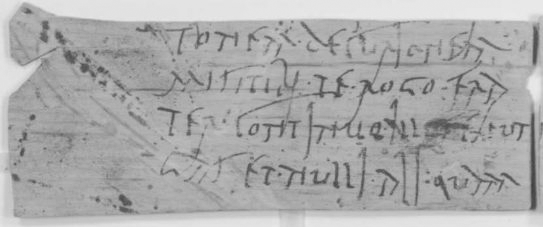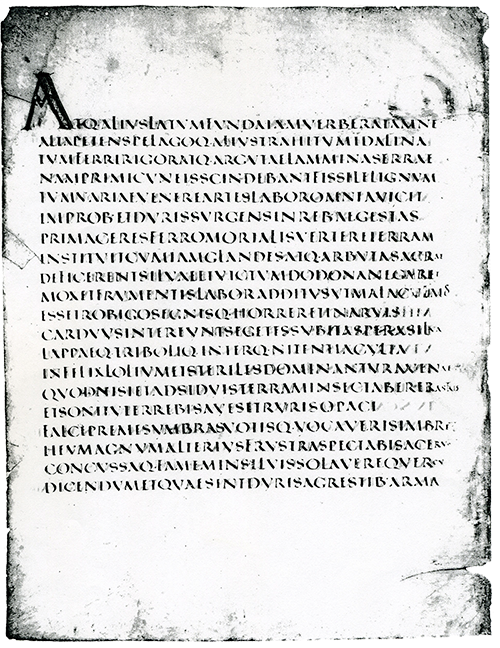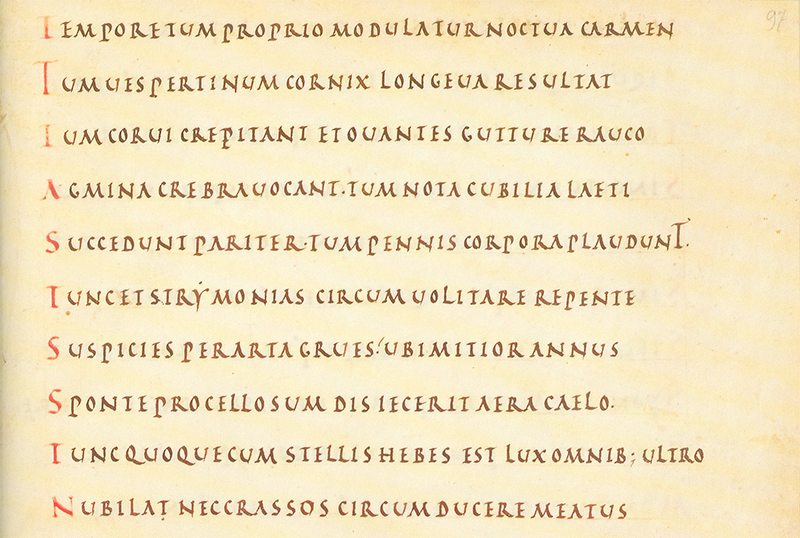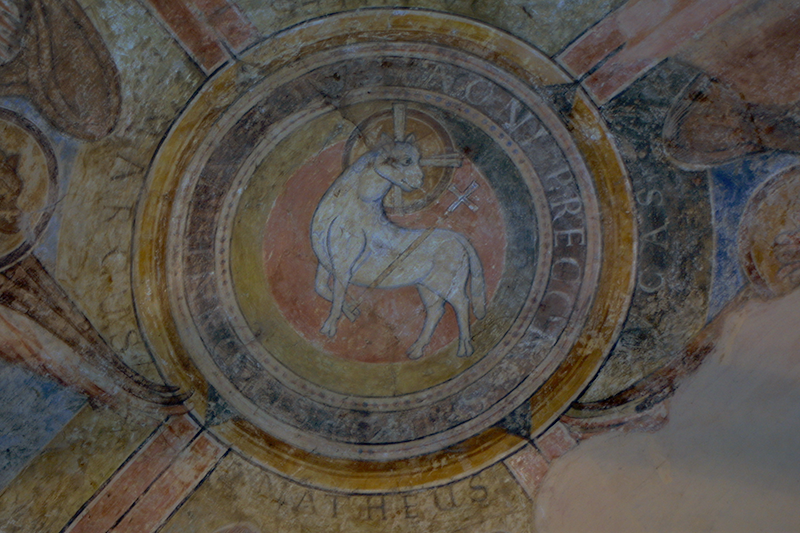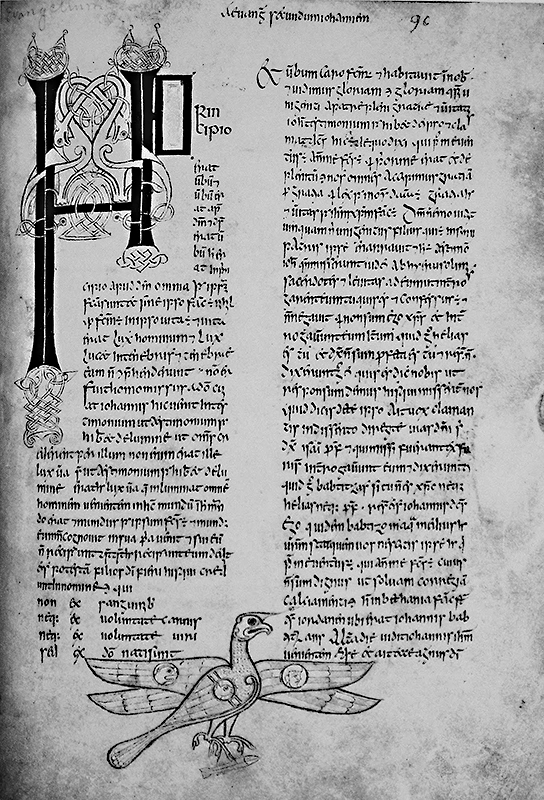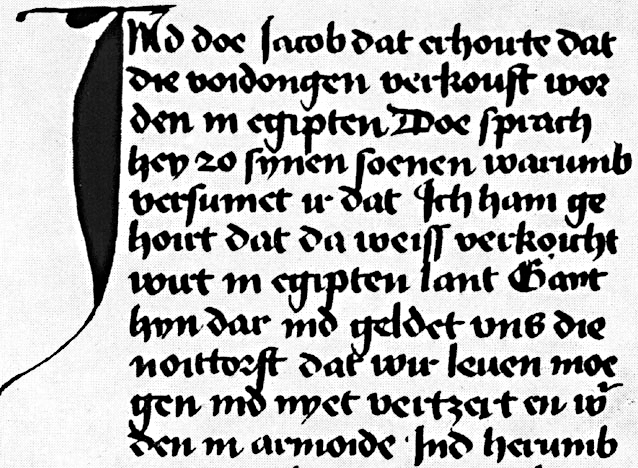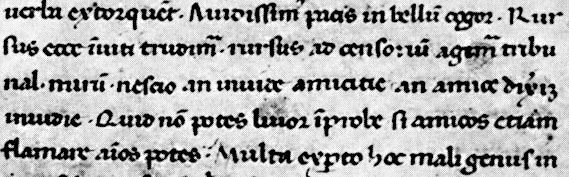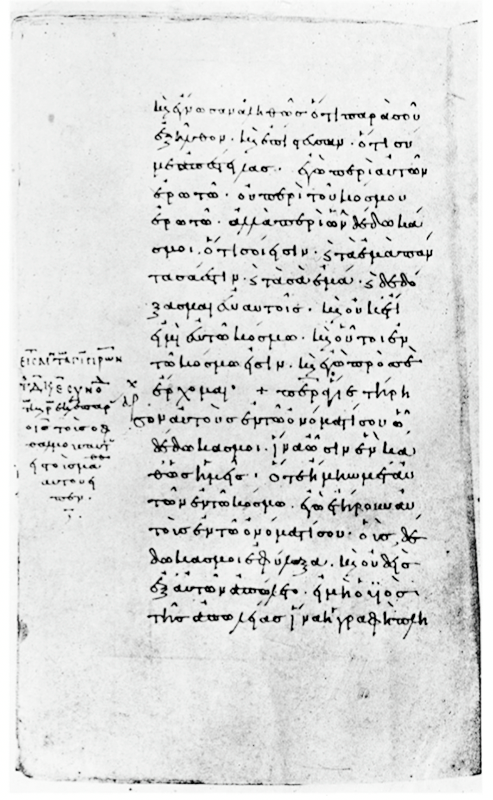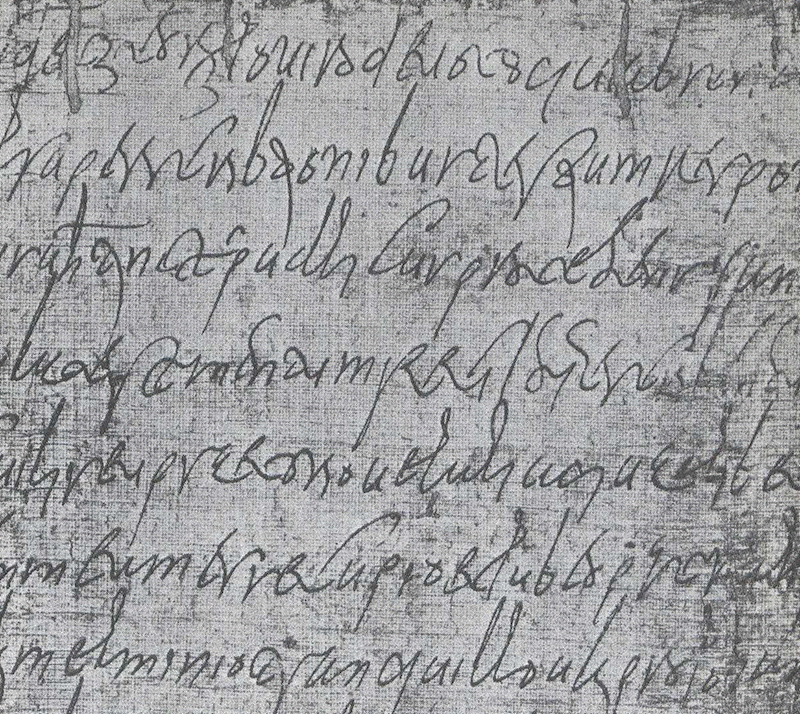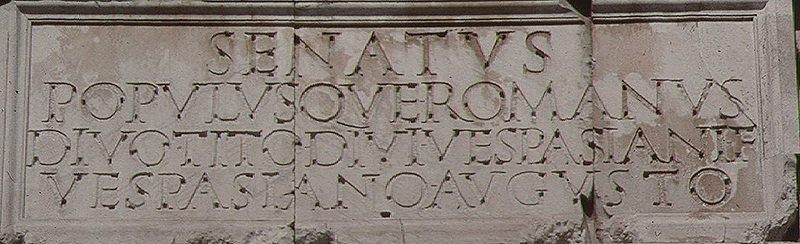
In den vergangenen Jahrhunderten war der Setzkasten mit
den Bleibuchstaben in zwei Bereiche unterteilt:
der
obere Teil war den Groß- und der untere Teil der
Kleinbuchstaben vorbehalten.
Aus dieser Zeit stammen im Englischen die Begriffe ‚uppercase’ für Großbuchstaben bzw. Majuskel und ‚lowercase’ für Kleinbuchstaben bzw. Minuskel.
Majuskel
Abgeleitet aus lat. ‚maior, maius‘ (magnus) = „groß“, (plural: Majuskeln)
Bezeichnet die Großbuchstaben des Alphabetes. Eine
andere verwendete Bezeichnung „Versal“
(plural: Versalien) betrifft eher die Anfangsbuchstaben
der Zeilen, Absätze, Verse. Eine Majuskelschrift
besteht ausschliesslich aus den Großbuchstaben und
bewegt sich auf dem Zweilinienschema (Obergrenze /
H-Linie und Grundlinie). Kapitälchenschrift, die
ebenfalls eine Majuskelschrift ist, bewegt sich hingegen
auf dem Dreilinienschema (Obergrenze / H-Linie, x-Höhe
und Grundlinie). Im Gegensatz zu den Kapitälchenalphabeten
ist die Buchstabengröße der Majuskelschrift
konstant.
Die Entwicklung der Majuskel teilt
die Paläografie in vier Phasen ein:
- Griechische Majuskel (9. bis 3. Jahrhundert v. Chr.). Aus dem Semitischen Alphabet wurden in Phönizien die Zeichen weitgehend übernommen; die Griechen haben um 900 v. Chr. dieses Konsonantenalphabet um die Vokalzeichen ergänzt, indem sie die nicht benötigten Zeichen umfunktionierten. Ob es sich dabei um eine Innovation oder Mißinterpretation handelt, bleibt in der Paläeografie umstritten. Bis zum Jahr 900 n. Chr. war das griechische Alphabet ein Majuskelalphabet.
- Römische Majuskel: (Capitalis)
(7. Jhdt. v. Chr. bis 5. Jh. n. Chr.). Die Griechen
tragen direkt im 7. Jahrhundert v. Chr. zur
Entstehung des altitalischen Alphabets bei. Die
etruskische Schrift bestand aus folgenden Majuskeln:
A B C D E F Z H I K L M N O P Q R S T V X und wurde
von rechts nach links geschrieben. Die Römer
übernehmen dieses Alphabet. In darauffolgenden
Jahrhunderten entwickeln sich folgende Formen des
„Abecedariums“:
- die Capitalis Monumentalis, meist im Stein gehauen; Die Buchstabenform geht von einem Quadrat aus; die Capitalis kennt weder Wortabstände, noch Silbentrennung. Aus diesem Alphabet entwickelte sich die uns bekannte Versalienschrift. Das bekannteste Beispiel für die Majuskelschrift ist die dorische Trajanssäule aus dem Jahr 113 v. Chr. Auch der aus dem Jahr 81 v. Chr. bietet eine gut erhaltene Capitalis Monumentalis.
- die Capitalis Quadrata leitet ihren Namen von der Form, aus der sich die Buchstaben bilden (Quadrat, Kreis, gleichseitiges Dreieck). Sie wurde für die Prachtbücher (Klassiker-Ausgaben) zwischen dem 1 und 6 Jh. n.Chr. verwendet. Vereinzelt findet man diesen Stil aber auch im 9. Jahrhundert.
- die Capitalis Rustica, die „Bäuerliche“ (‚rusticus‘ = „ländlich, bäuerlich“), wurde für weniger prunkvolle Bücher vorwiegend zwischen dem 1. und 5. Jahrhundert n. Chr. verwendet. Sie war durch ihre schmale und kurvige Formgebung für die zügige Notation geeigneter als die Quadrata oder Monumenatlis. Aufgrund ihrer Verbreitung und Popularität in der Antike wird sie von der Paläografie gern auch als kanonisierte Capitalis bezeichnet.
- die ältere römische
Kursiv ist der Vorläufer der
Minuskel. In der paläografischen
Entwicklung zeigt sie erstmals die
Drei-Zonen (Ober- und Unterlängen), die
später das Merkmal der Minuskel sein
werden. Die Capitalis cursiva ist als alltägliche
Gebrauchsschrift vorwiegend für Korrespondenz
und Geschäftsbriefe zwischen dem 1 und
4 Jh. n. Chr. verwendet worden. Eine
interessante Sammlung der römischen
Tafeln zeigt das
Vindolanda-Projekt
(antikes Römerlager in Vindolanda b.
Newcastle / Norden Englands).
- Unziale (4. bis 8. Jahrhundert n.
Chr.) und Halbunziale. Diese runde Schriftform
entstand im Verlauf des 4. Jahrhunderts und wurde
bis zum 8. Jahrhundert für den Fliesstext von
vielen Buchmanuskripten (Codices) verwendet. Sie
wurde mit der Rohrfeder auf Pergament geschrieben;
wir kennen sowohl lateinische als auch
griechische/byzantinische und kyrillische Formen. Es
sind nur circa 300 Manuskripte, meist Teile der
Bibel, in Unzialschrift erhalten. Vollständig
erhalten sind beispielsweise der Codex
Sinaiticus (
Codex
Sinaiticus Projektseite)
und der Codex Vaticanus. Ähnlich wie die
Capitalis Quadrata, beginnt die Unziale ihre „kalligraphische
Karriere“ als reine Buchschrift, doch sie
wurde auch in Stein gemeisselt und in Metal geform.
Die Stationen der Entwicklung der Unziale zeigen
noch zwei bedeutende Etappen, die keine funktionale
Verwandschaft mit der Urform zeigen. Nach 800 wurde
sie nur noch als Auszeichnungsschrift verwendet, für
prunkvolle Titel und Untertitel. Hier beginnt sie
Farbe anzunehmen; sie wird nicht nur in Rot, sondern
auch oft in Blau und Grün geschrieben –
Im 14. Jahrhundert wurde als Vorläufer der Antiqua die Buchschrift Gotico-Antiqua oder Fere humanistica geschaffen, indem Elemente aus der Antiqua zur Verschönerung der gotischen Schrift verwendet wurden. Die Vielfalt wird durch die allgemeinere Schriftlichkeit noch gesteigert, da jetzt in den gotischen Kursiven (Notulæ genannt) auch eine Geschäftsschrift entsteht. Diese Kursiven hatten kleinere, flüchtigere und verbundene Buchstaben, deren Oberlängen als Schlingen und Schleifen ausgebildet wurde. Auch die Nutzung von Papier bedeutete für die Textura eine einschränkende Nutzung, da sie für Papier wenig geeignet war. Die Kursiven haben dann Einfluss auf die Buchschriften genommen und so haben sich aus dieser Mischung die verschiedenen Bastarden ausgebildet, die in vielfältigen Spielarten verwendet wurde. Als Beispiel ist hier die Fraktur (langes s und f sind charakteristisch) zu nennen. Die Bastarden zeichnen sich durch spitzbögige Rundungen und Köpfe an den oberen Schaftgabelungen aus. (w. o., vgl. auch: Bischoff: 163-186, Brandt: 77, Foerster: 196-215, Goetz: 340.)